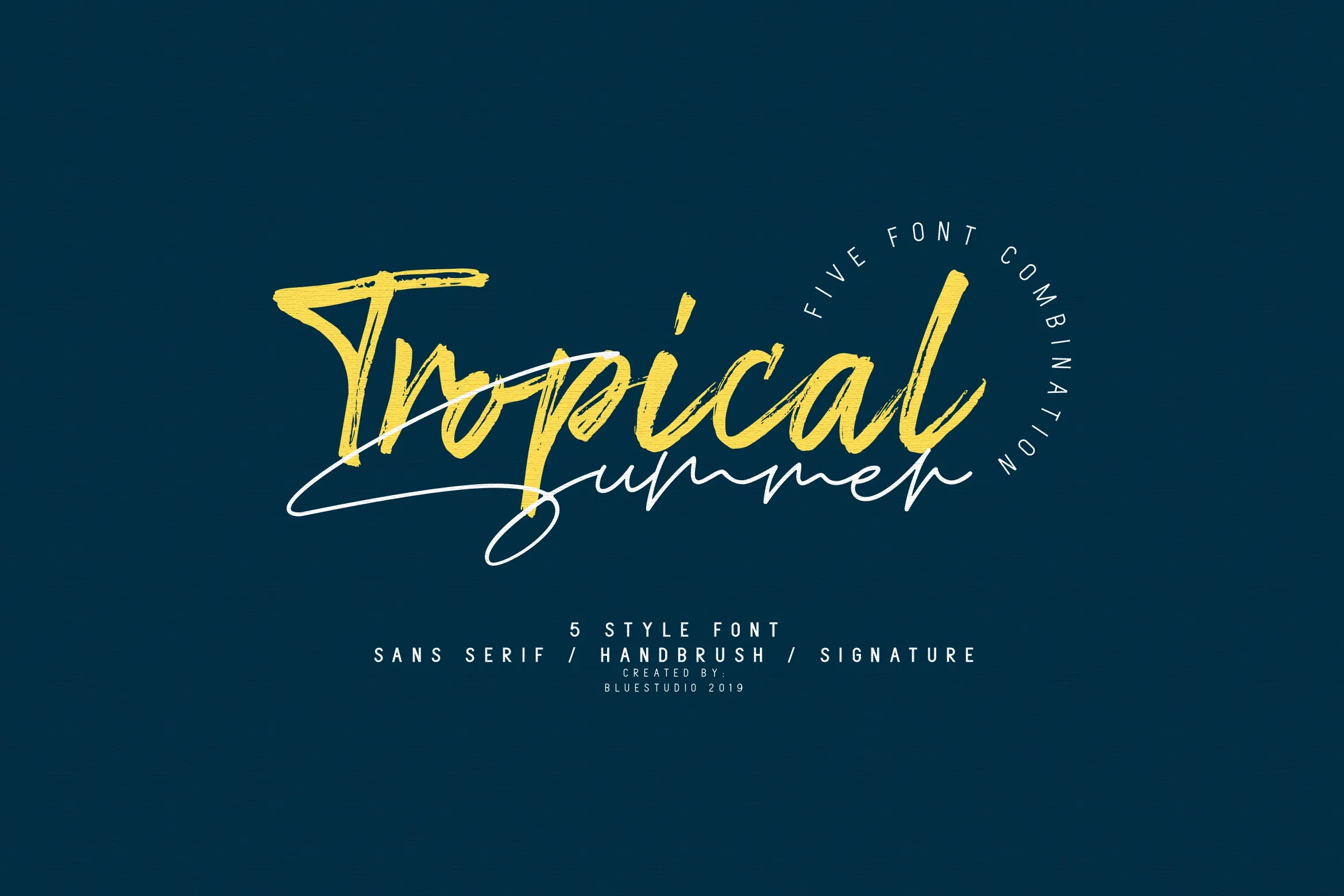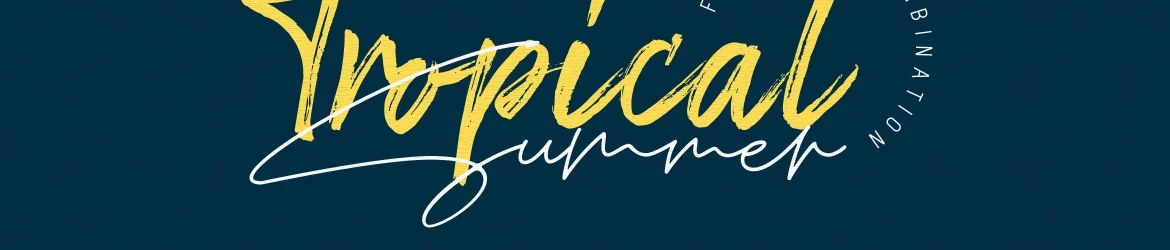
Tropical Summer é uma deliciosa escolha para quem busca uma mistura suave entre script e fontes geométricas. Fabricada pela bluestudio, esta fonte script simples mas única oferece um formato limpo e traços leves, combinado com elementos fun e ligaduras sutis que dão um toque de personalidade ao seu design. Perfeito para uma ampla gama de projetos gráficos como logos, marcas, capas de livros, postais, convites de casamento, cartões de agradecimento, citações e muito mais, Tropical Summer é uma fonte script ideal que adicionará um toque único ao seu próximo projeto. Quebre o gelo com sua graça exuberante ou deixe seus designes conversarem diretamente com quem você está criando para. Envolva a sua comunicação visual em cores e formas vibrantes de verão tropical com Tropical Summer.